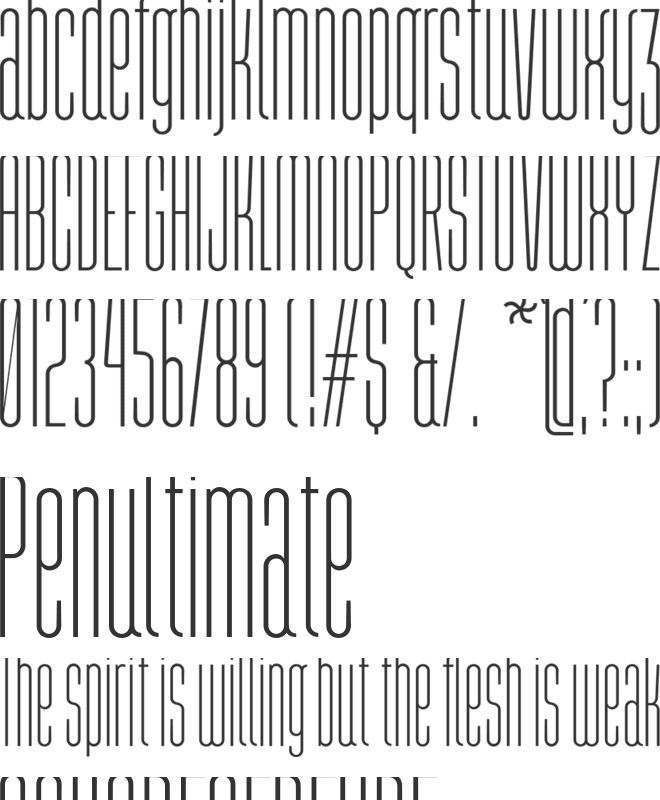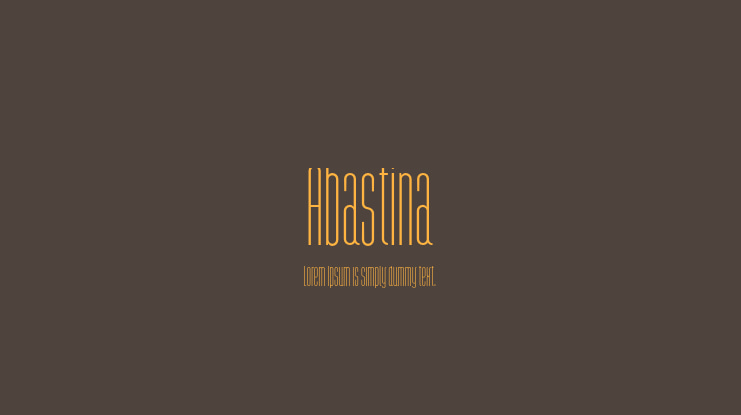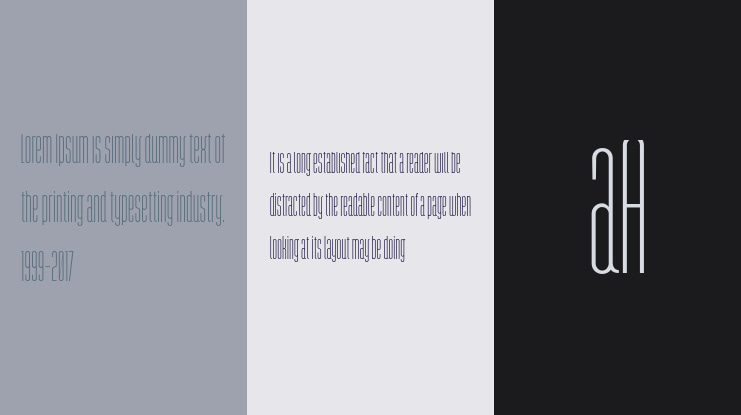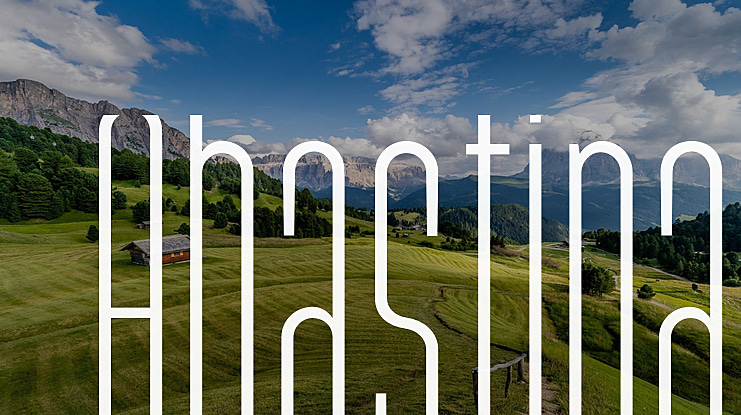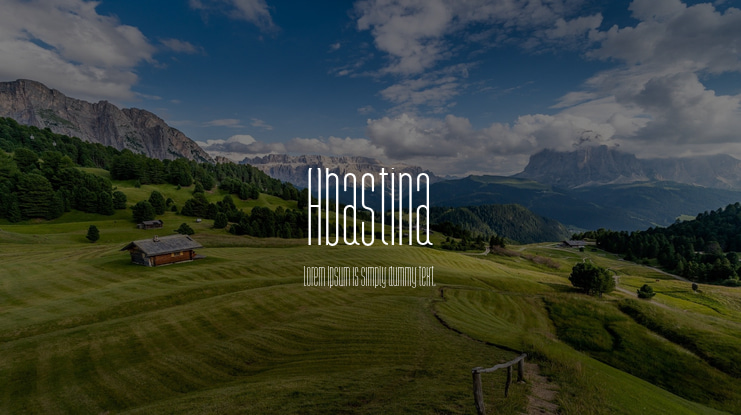
Abastina Font
Matias Castro & Sebastián Asegurado
Abastina es una tipografía para títulos y textos cortos. Está basada en la arquitectura del Mercado del Abasto en Buenos Aires Argentina. La tipografía es gratuita para uso no comercial de ser así contactarse con nosotros.